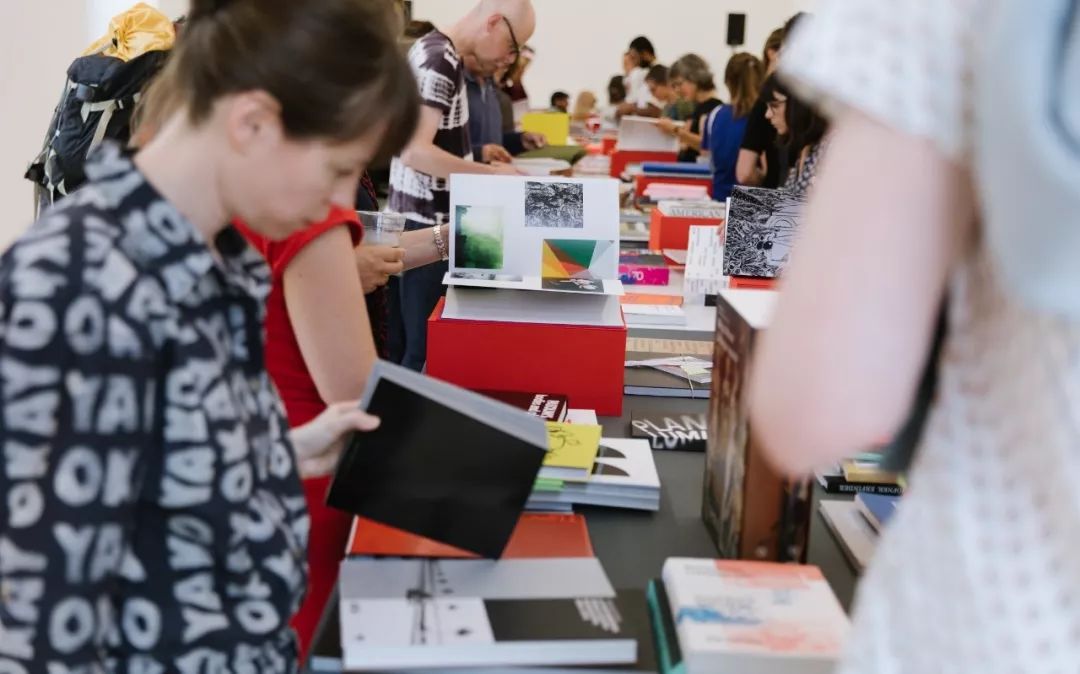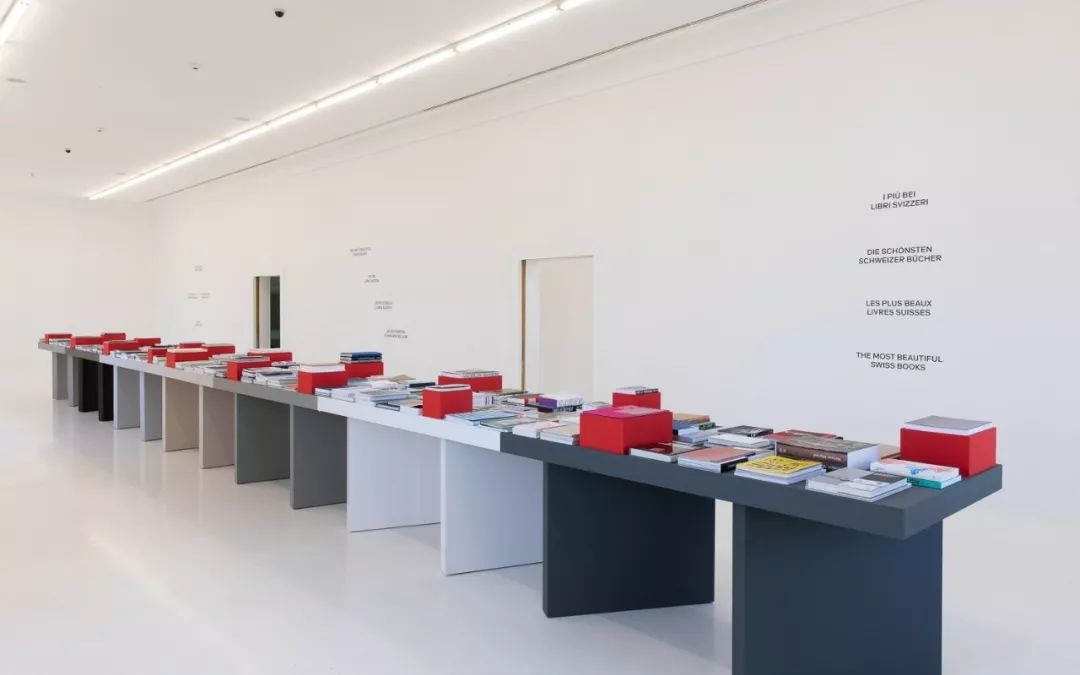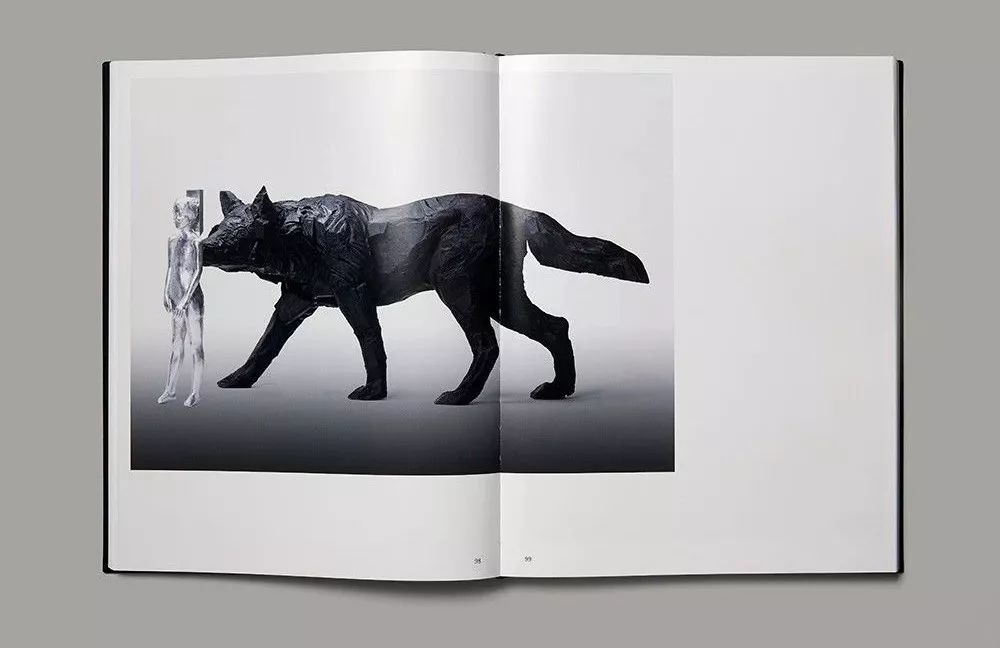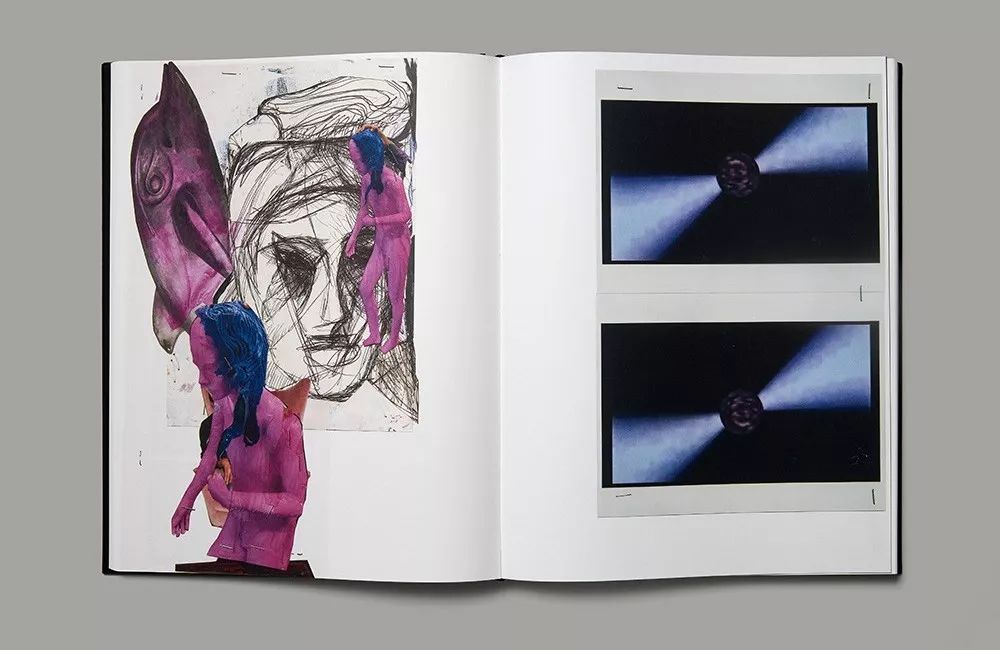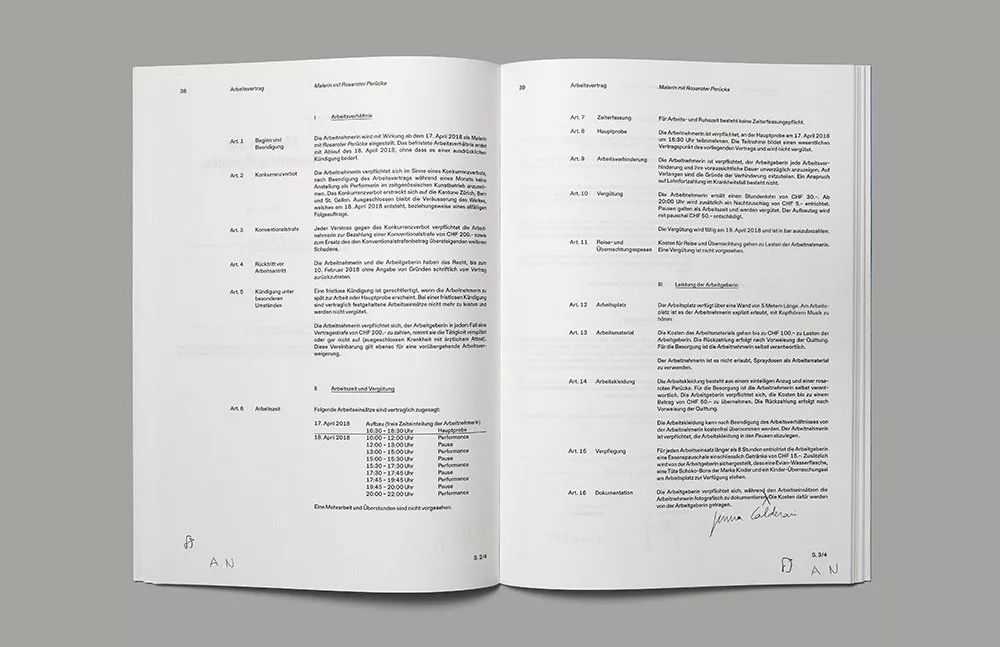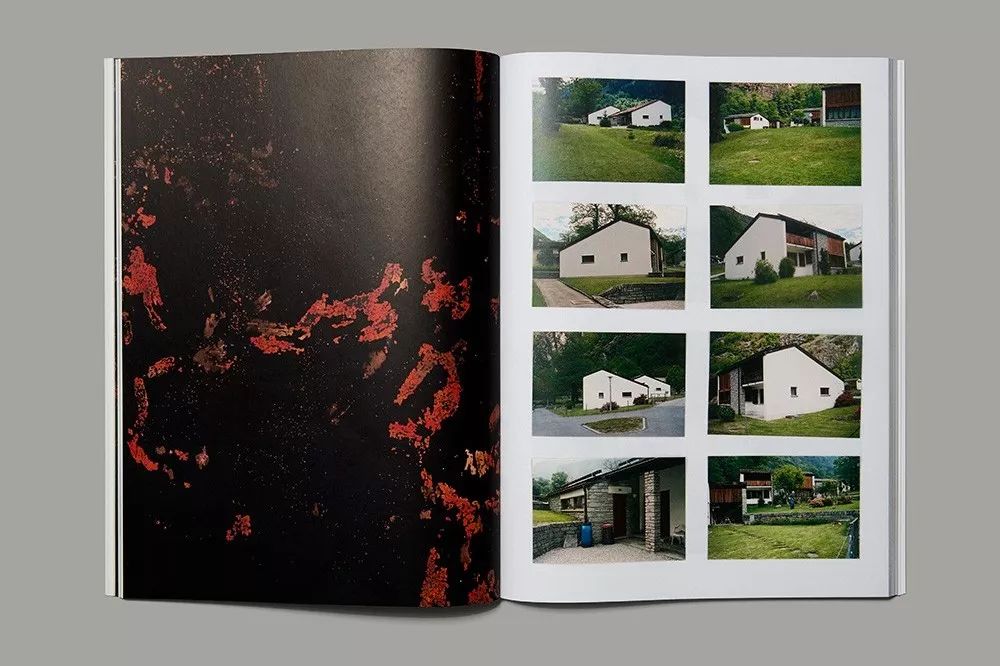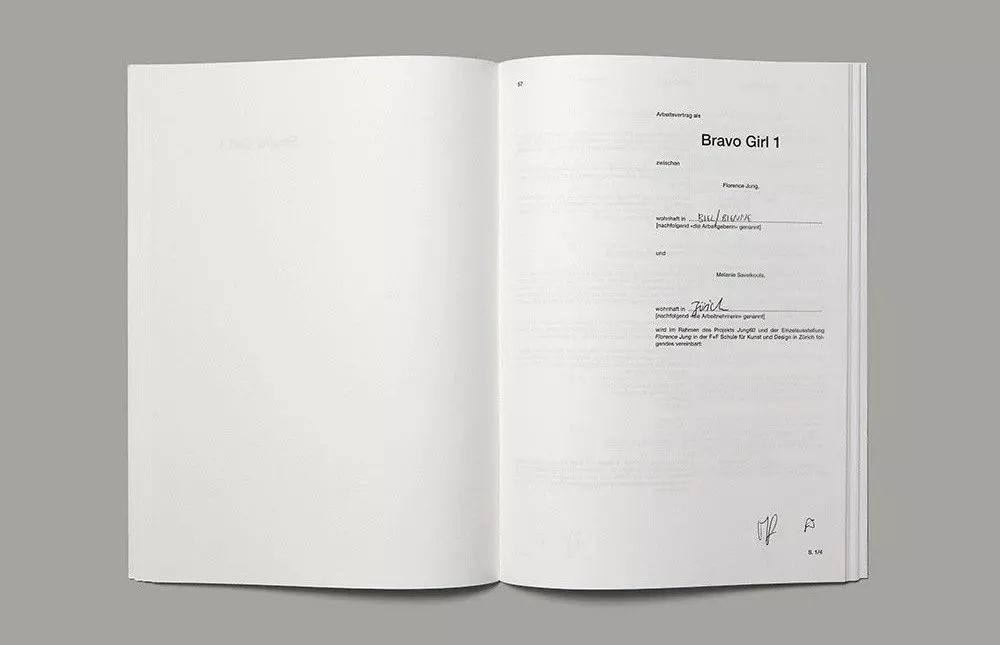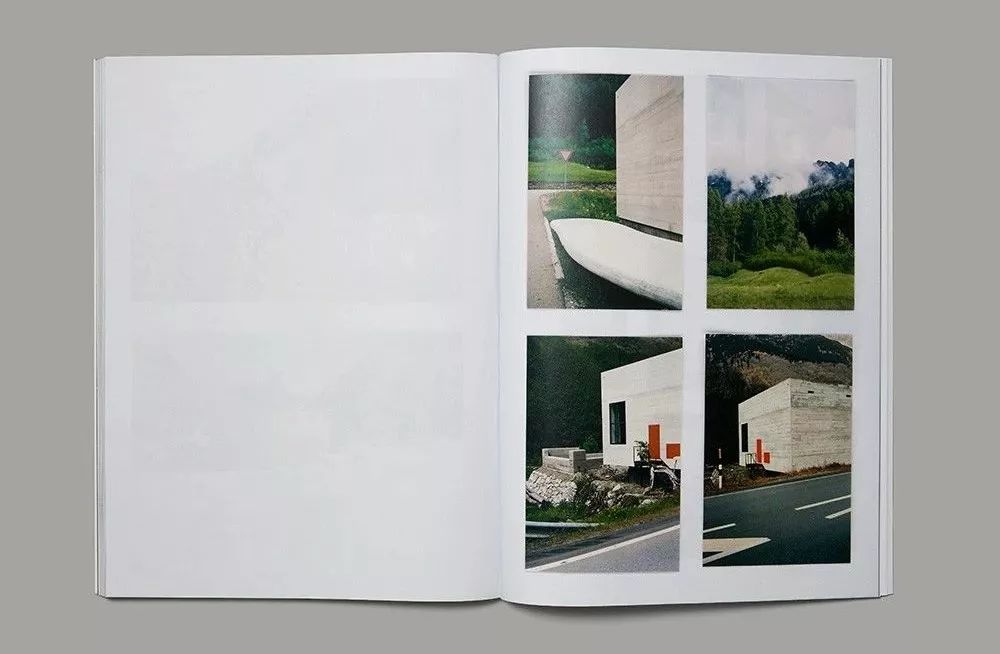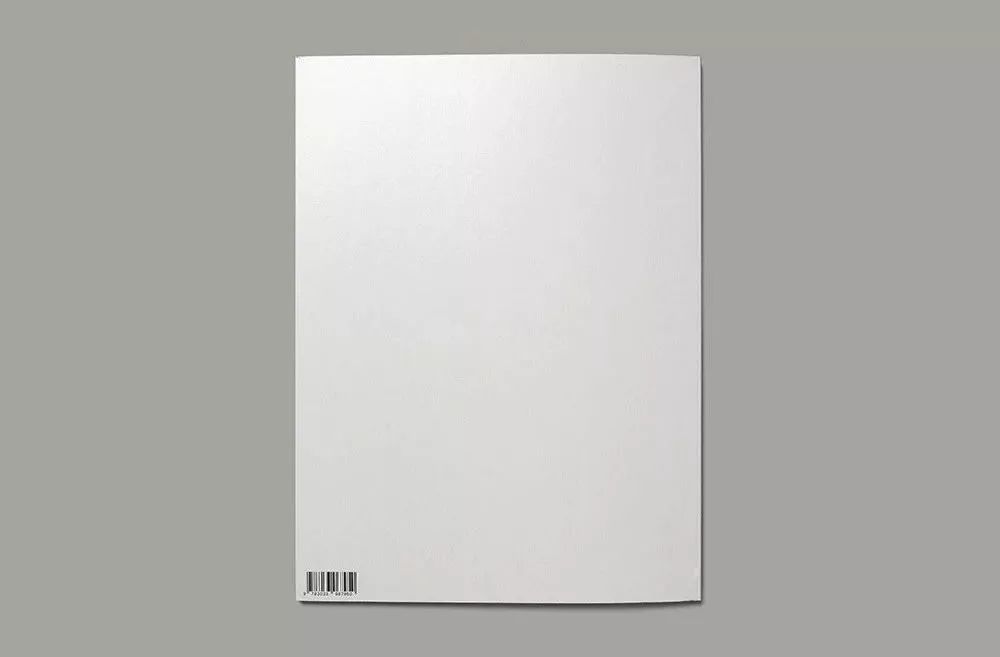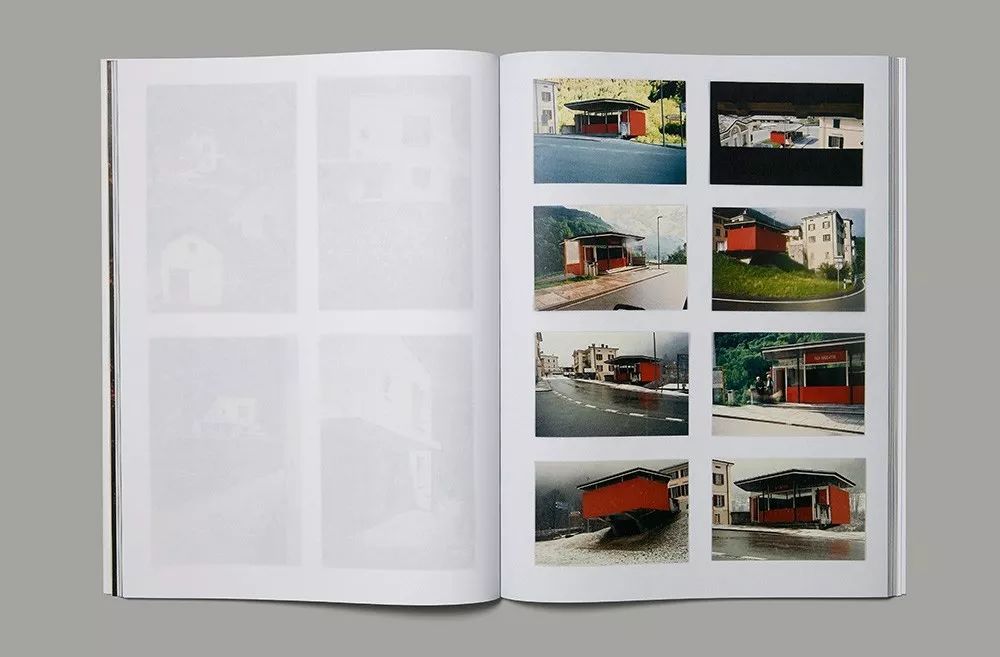
“瑞士最美的书”,19本惊艳亮相!
“瑞士最美的书”是每年都会举办的老牌评选,自1998年起,联邦文化办公室接管了瑞士书商和出版商协会之前组织的“最美瑞士图书”竞赛的协调工作。从那以后,赛事经历了战略内容和评判标准的调整,更加强调设计方面。
BAK作为举办方,它注重书籍设计和制作方面的卓越表现,精选出表达高质量内容的作品。2018年19本最美的书由BAK根据由平面设计师Gilles Gavillet主持的五人评审团的推荐颁发。(书籍出版于2018年,于2019年评判)
虽然内容领域不尽相同
但有各自出彩的排版和设计
Architektur-theorie im deutschsprachigen
Kulturraum1486-1648
这本蓝色压花精装书收录了一千多篇关于早期现代建筑理论的著作,是一个非凡的、完整的知识储存库。书中对作者和建筑的详细图文介绍,使用了巧妙的排版布局及检索系统,标题和页边距也进行了精心设计,它集中体现了书作为媒介的本质功能。
The University is now on air
该出版物的主题是1890-1939年建筑学和设计史的大学课程,该课程由1969年成立的开放大学于1975年至1982年间在英国广播公司播出。书中包含了丰富的插图解说、四篇关于历史背景的随笔,以及五篇与相关人员的对话。对今天的读者来说,这是一个动态的、广阔的、高度吸引人的图像和文本叙事。
Film Culture 80.
The Legend of Barbara Rubin
这本书关于颇具影响力的纽约电影艺术家芭芭拉·鲁宾(Barbara Rubin, 1945-1980年),包含了信件的重印和其他极具参考价值的历史材料,并提供了对她的私人世界的独特见解。
I Fuck With Turrell
Ne travaillez jamais
这是一本小巧的软皮书籍,被打造成一个在艺术和研究之间的领域,是一个合作探索的游戏空间。设计师在编辑层面上做了很多工作,布局和排版也是如此细致地执行。
Andro Wekua
来自乔治亚州的艺术家安德罗·威库亚(Andro Wekua)的全部作品都被收录在这本书中,书中精妙的排版设计使作品达到了最佳呈现效果。这本红黑相间的精装书在这位艺术家的名字下面印有丝网印刷的拼贴画,抓人眼球,内部的设计却是平静和极具空间感的。
Bildrausch
Drawings 1966-2018
72岁的苏黎世摄影师沃尔特·法伊弗(Walter Pfeiffer)此前并不为人所知,他的作品被制成了一本大画册,封面色彩极其鲜艳。设计不是强加于作品之上,而是与之结合,相互成就。
SAMMLUNG
Christoph Kappeler
这是一册私人艺术收藏文件,大部分内容由白色的双页纸组成,通过像挂在墙上一样呈现图像,将馆藏的空间性转化为书籍的形式:在每双页纸上,自由排列着多幅不同大小的作品。
147 Backcovers
Summer Fall Winter Spring
这本由彼得·菲什利(Peter Fischli)和希拉尔·施塔特勒(Hilar Stadler)合著的概念高度抽象但又颇具娱乐性的艺术家书籍,收录了布鲁诺·比斯霍夫伯格画廊(Galerie Bruno Bischofberger)自1987年以来在美国杂志《艺术论坛》(Artforum)上刊登的部分广告。在这本模仿杂志格式的书里,所有的广告都印在右边一整页纸上,这让人想起了盗用艺术。简约的设计完全没有任何标题、评论甚至页码,该书摒弃了传统的标题页,直接从第一个示例开始,因此本质上使其类似于一叠纸。然而,一个非传统的标题页,包括信息和colophon,可以发现在封底——正是广告最初出现的地方。其结果是对艺术与广告、高雅文化与流行文化之间关系的有力陈述。
Florence Jung
Jung从苏黎世F+F学校招募了12名艺术设计专业的学生,让他们在一系列的表演中扮演“有抱负的画家”、“特别感兴趣的艺术家”和“优秀的女孩”等角色。作为他们的雇主,她与所有表演者签订了详细的合同,内容涵盖从报酬到演出时间、餐饮等方方面面。这本书涵盖了12份合同,其中一些是手写的补充。合同是完整打印的,没有任何改动,艺术品和书籍设计之间的界限就变得模糊了——这主要是因为原件的排版非常巧妙。
Verde
关于布雷加利亚山谷十年来的建筑和景观的摄影文献以一本普通的摄影书的形式呈现出来,图片有规律地排列在右侧,与通常厚重的咖啡桌上的大书相比,这是一个令人愉快的变化。
FOR A FISH TANK OR A PARKING LOT
在这近500页的手稿中,每一页都有9张黑白照片,照片上的每一块石头都是按照严格的规则排列的。完全缺乏信息会导致迷失方向,但单个石头之间的差异是可以观察到的。这本书就被视为一件艺术品本身,可读性似乎是一个相当次要的目标。
Der Durchschnitt als Norm
一本黄色软皮书讲述了苏黎世艺术家迈耶和弗朗茨对公共空间的微妙干预,这看似是一本相对传统的文本书籍,以单列的形式呈现苏黎世城市环境发展的对话和论文,偶尔穿插黑白插图,但透出巧思:使用薄、高光泽的特殊纸本和反向切边。
Tree Identification for Beginners
An Ideal for Living
行为艺术家Alexandra Bachzetsis和设计师Julia Born展示了一本细长的、极具特色的书,贯穿全书的是亮眼的特调橙黄色。虽然它是为了配合展览而制作的,但它通过将作品的各个部分从表演媒介具体地调整到图书媒介,创造了一种新颖的呈现方式。页面的简单交错将两层文本和两层图像交织在一起,形成了不同于声音和手势的戏剧效果。
We say we are fine
They say we are not
这本44页的出版物展示了在一项艺术研究项目中发现的现象,该项目调查了上世纪80年代和90年代瑞士人民与南非种族政权之间的各种关系。
Color Library
43–35 10TH STREET
这本尺寸不大但很有分量的艺术书籍,有一个棕色硬纸板折叠封面和瑞士版装订方式,呈现了美国作家丹尼尔·谢伊(Daniel Shea)关于城市规划、建筑工地和中产阶级的多面摄影散文。
Giftmord
Eine Kriminalgeschichte von 1929
在虚构的人生故事和历史文献中,作者探讨了一位16岁的母亲的案例,她被指控是女巫,尽管她坚称自己无罪,但1929年在阿劳因双重谋杀被判终身监禁。
Peter Halley
Paintings of the 1980s:
The Catalogue Raisonné
这是美国画家彼得·哈雷(Peter Halley)的创作合辑,全面反映了他作品的概念和历史背景。从1980年到1989年的186幅画作中,有许多是用高纯度颜料绘制的。这本书以方形格式呈现,严谨的结构布局、大面积的空白,以及基于原始图纸的Helvetica新数字化版本,有明显的瑞士设计特点。